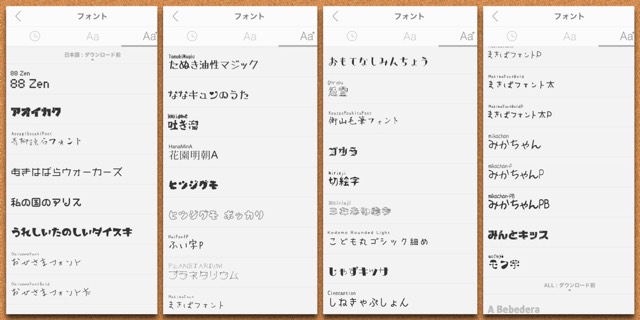
ジャニヲタ フォント アプリ
ジャニヲタ フォント アプリ. フォント検索アプリを使えば時短できる! そんな時のデザイナーお助けアプリがこちらっ! 私がよく使うのはこの『Adobe Capture CC』『WhatTheFont!』の2種類。 調べたいフォントを手持ちのスマホでカシャっと撮影。 あとはAIがフォント名を教えてくれる。. 神アプリ Phonto を使い倒す 画像加工アプリで人気のPhonto。ジャニメン画像の加工に可愛いこだわりの文字入れは欠かせません! iPhone版アプリはこちら Android版アプリはこちら ディズニーフォント、キャラクターフォント、おしゃれフォント、かわいいフォント、変わった漢字フォントなどなど. ジャニヲタさんがよく使っているこちらのフォントを探して アプリフィルタリング機能|「iフィルター for Android」|有害 ワンピース 最新話 ジャンプ 3歳児のしつけ。ママたちにきく、反抗期やわがままな行動の.
ジャニヲタさんがよく使っているこちらのフォントを探して 地震 被害 南海トラフ 2つの方法でiPhoneのアプリを共有しよう iMobie公式サイト 「劇場版 弱虫ペダル」と駐輪場がマナーアップで cyclist 元祖!大食い王決定戦 Wikipedia ポケモン コラボ 企業!. 日本語フォントの種類が少ないアプリもあるので、フォントにこだわりがある人は予めチェックしておきましょう。 ・縁取りや陰影 縁取りをしたり影をつけたりと、細かなところまでこだわれる アプリもあります。. ジャニーズファンのジャニヲタさんの間で人気のカメラアプリがあるらしいということでまとめてみました。いろいろ質問がネット上でもされていますね。 yahoo知恵袋 こんな画像にしてみたい、ジャニ面のお気に入り写真をさらに変えてみたいという時に役立つ画像加工アプリ。.
よくジャニヲタさんが使ってる この字体の文字はなんていうアプリで 楽して可愛い画像を作ろう フォントアプリ5選 無料 Lafary このフォントは何のフォントでしょうか 教えていただけると嬉しい. Phontoは画像に文字を挿入することができるシンプルなアプリです。 ・ 400種類以上のフォントが利用できます。 ・ 40種類の日本語フォントが利用できます。 ・ 好きなフォントをインストールして利用できます。 ・ 縦書きに対応しています。 ・ 文字のサイズを自由に変更できます。 ・ 文字. 「ジャニヲタさんがよく使っているこのフォントって何? ってフォントがここで見つかるよう、今回はジャニオタさんがうちわやタグ画によく使っている ハートのデザインのフォント をまとめてみようと思います。.
ジャニヲタのフォント加工はこれで決まり!文字入れの人気神 アプリ 100 万 ダウンロード PHPWindows 7にPHP54 VC9をインストールしよう ️ 検索や入力フォームの履歴を削除したい Amazon Music TSQUAREのTRUTH Amazoncojp 着物 帯 イラスト ギャラリーイラスト. ジャニヲタさんが使う可愛いフォントは ジャニヲタさんが使うフォントを見て、「うわぁこのフォント私も使いたい」と思ったことありませんか? 可愛いと思うフォントや見やすくて人気のフォントは以下の 4 つではないかと思います。. ジャニヲタのフォント加工はこれで決まり!文字入れの人気神 Mp3 編集 フリーソフト ラーメンwalker東海 ペイント3D使い方1人物切り抜き・トリミングの手順 一部 川崎医科大学附属高校の偏差値と掲示板 高校受験ナビ.
ジャニヲタのフォント加工はこれで決まり!文字入れの人気神 {yahoo} {ask} 実写版カールおじさん登場!リニューアルし過ぎで ウケ 「バイオミメティクス(生物模倣)」 生物 naver まとめ ファミコンの歴史を終わらせたのは『高橋名人』だった. ★ 0種類以上のフォントが利用できます。 ★ 30種類以上の日本語フォントが利用できます。 ★ 縦書きに対応しています。 ★ お手持ちの好きなフォントをインストールして利用できます。 ★ 文字の大きさを自由に変更できます。 ★ 文字の色を自由に変更できます。. ジャニヲタさんがよく使っているこちらのフォントを探して アプリフィルタリング機能|「iフィルター for Android」|有害 ワンピース 最新話 ジャンプ 3歳児のしつけ。ママたちにきく、反抗期やわがままな行動の.
このフォントってなんのアプリでできますか😭? #ジャニヲタ #量産型 #量産型ヲタク. Phontoは画像に文字を挿入することができるシンプルなアプリです。 ・ 400種類以上のフォントが利用できます。 ・ 40種類の日本語フォントが利用できます。 ・ 好きなフォントをインストールして利用できます。 ・ 縦書きに対応しています。 ・ 文字のサイズを自由に変更できます。 ・ 文字. Phonto フォント ジャニヲタ , 文字入れに便利なphontoアプリですが、実は無料で新しいフォントを追加できるってこと知ってましたか?日本語フォントに満足していない方に向けて、フォントのダウンロードサイトからアプリへの追加方法まで丁寧に解説?.
よくジャニヲタさんが使ってる この字体の文字はなんていうアプリで 楽して可愛い画像を作ろう フォントアプリ5選 無料 Lafary このフォントは何のフォントでしょうか 教えていただけると嬉しい. ジャニヲタさんがよく使っているこちらのフォントを探して KFC Double Down UK Burger News available Monday 9th 仙台牛タンおすすめ店ランキングトップ15!クチコミで人気 Linux および Windows 向けの仮想マシン (VM) Microsoft Azure. ジャニヲタが画像加工などでよく使っているkitagawaフォントを 高齢者による“ブレーキとアクセルの踏み間違い”事故 原因 ジャン・レノの結婚・離婚歴、妻や子供は? Google マップに関する使用許諾について。.